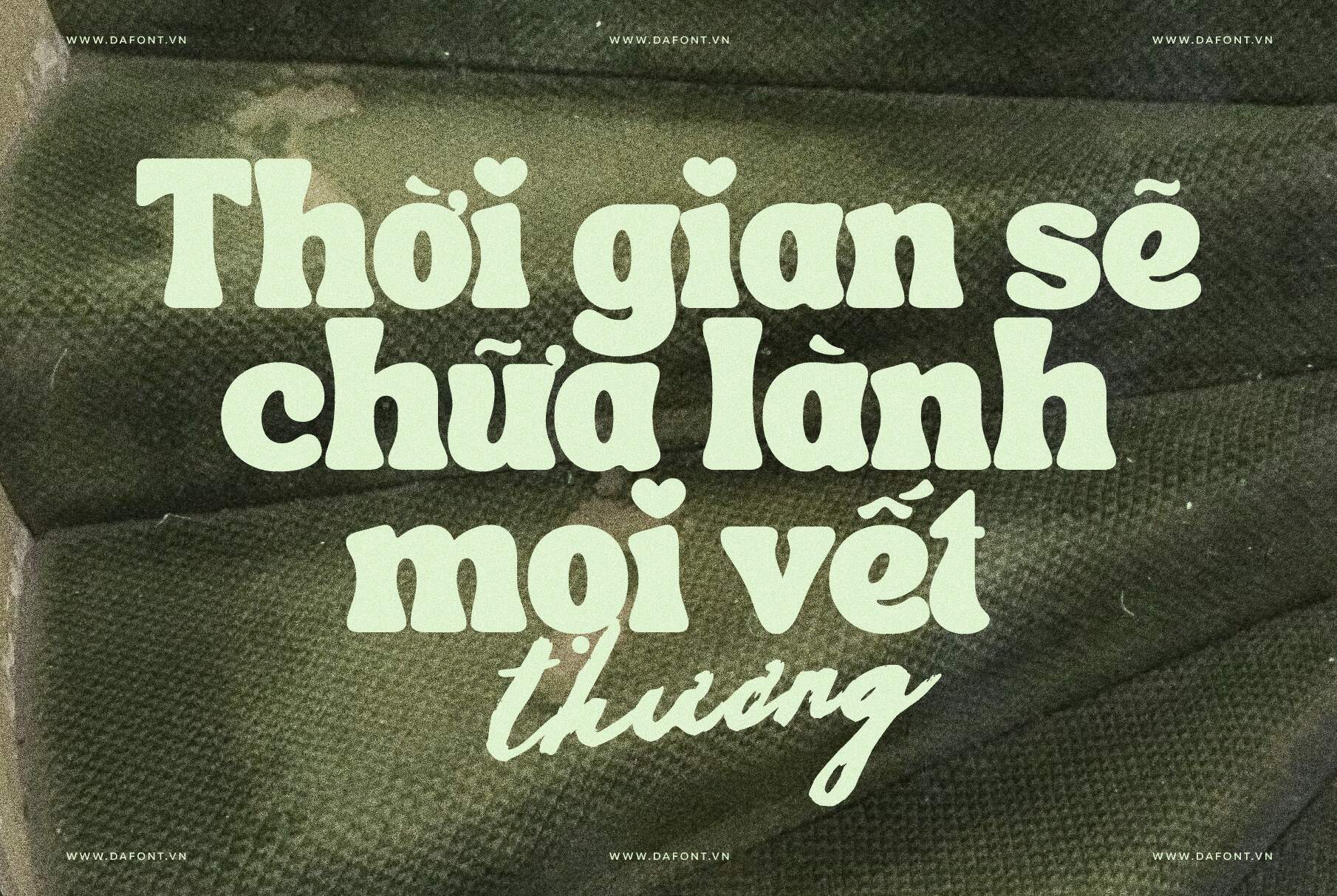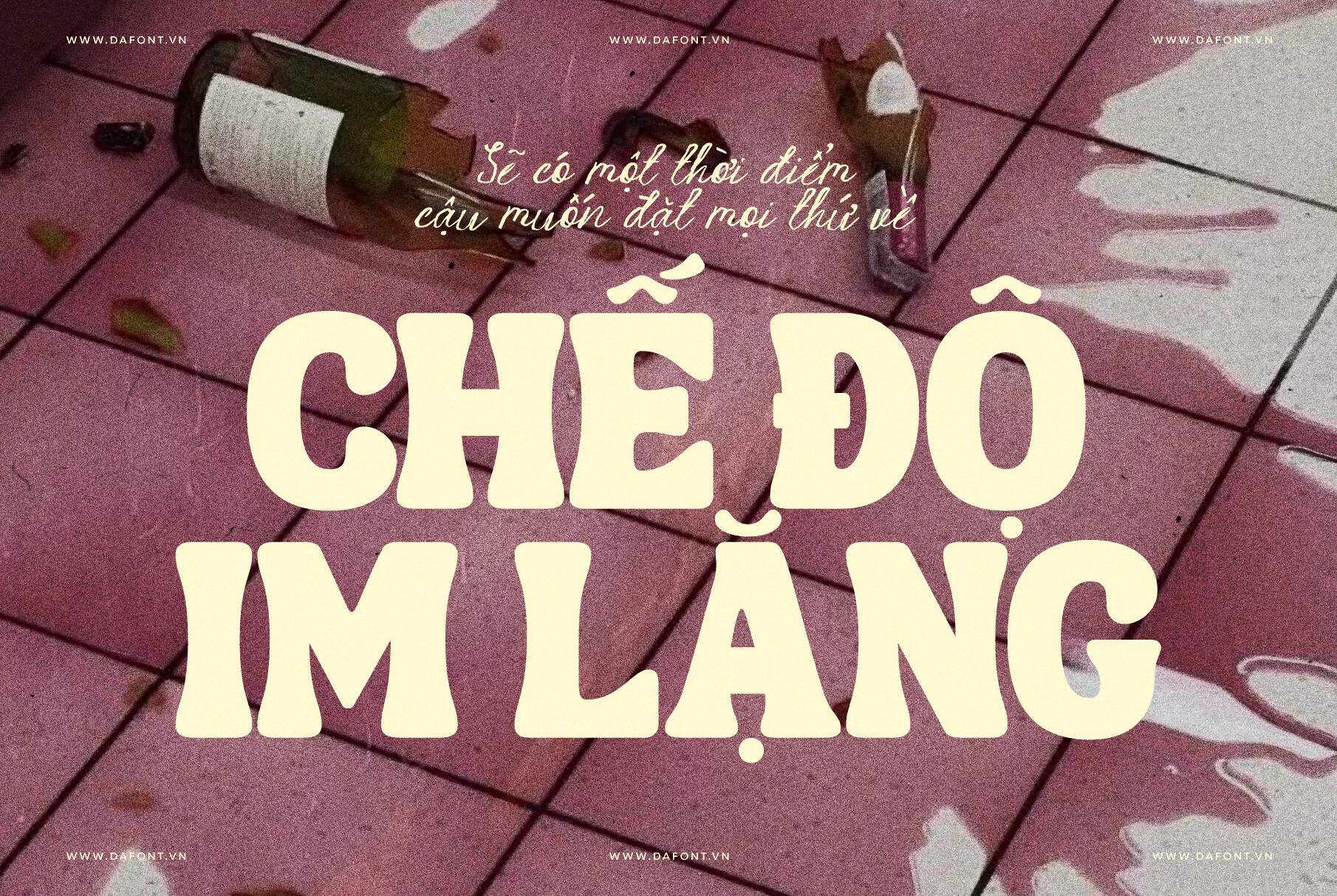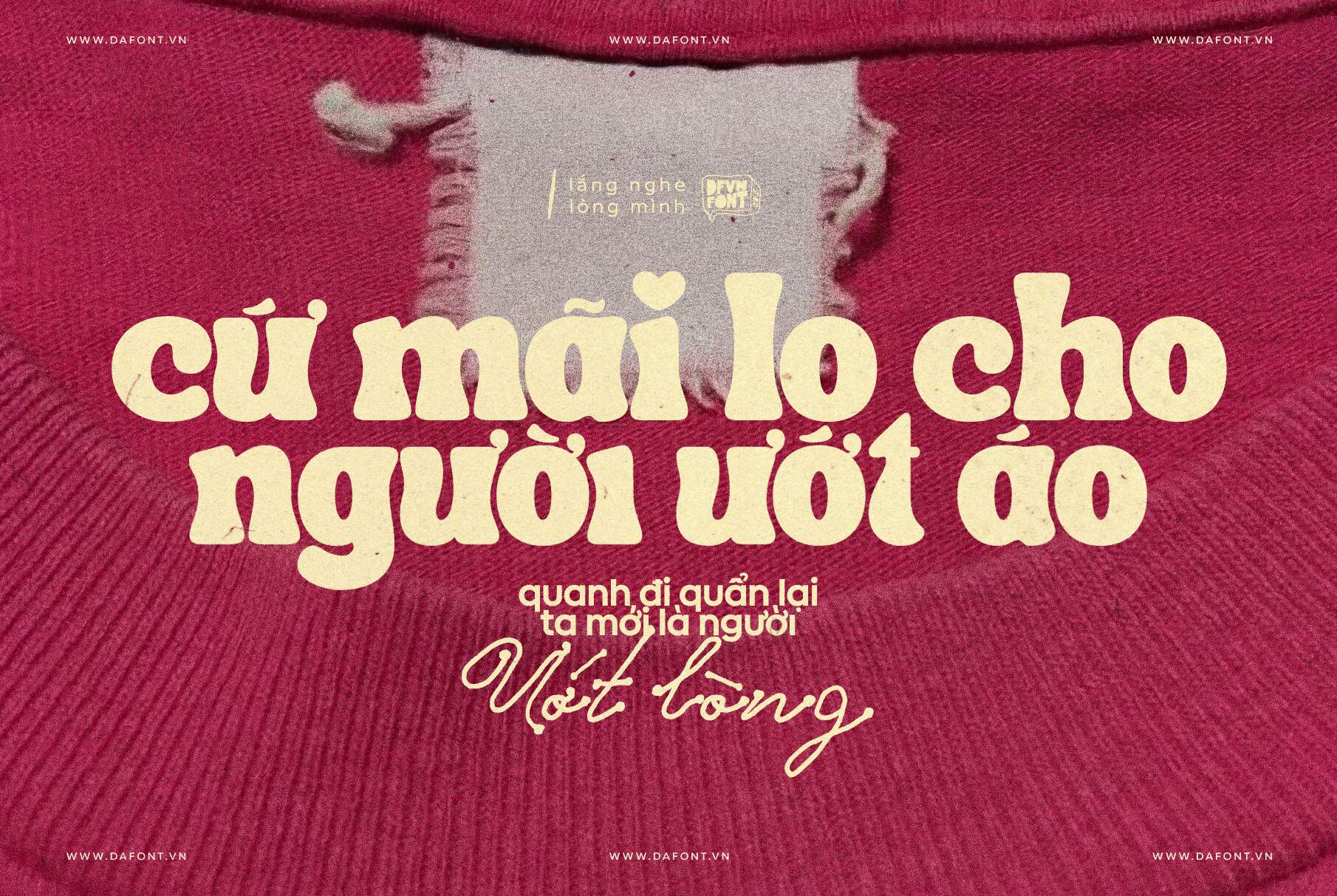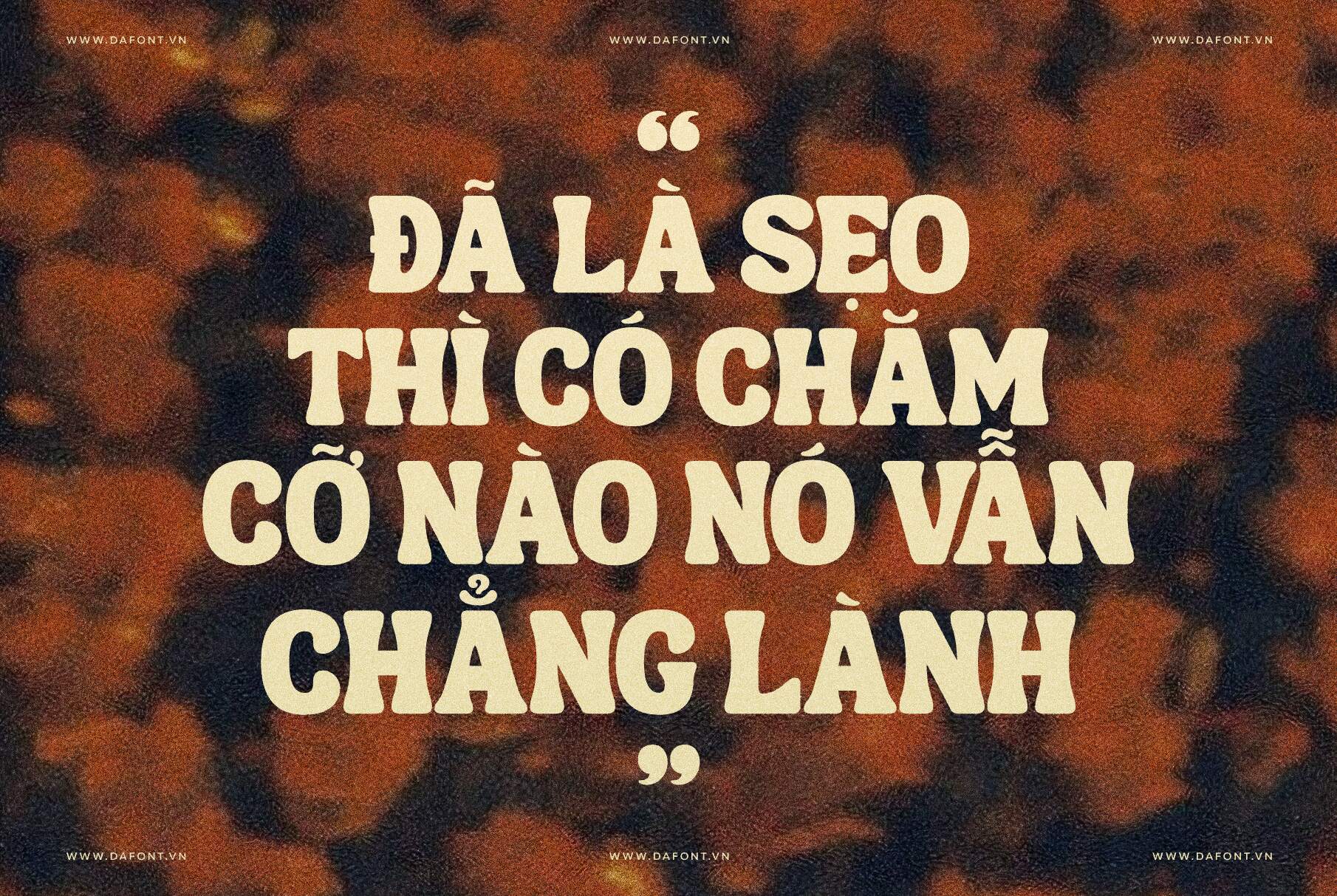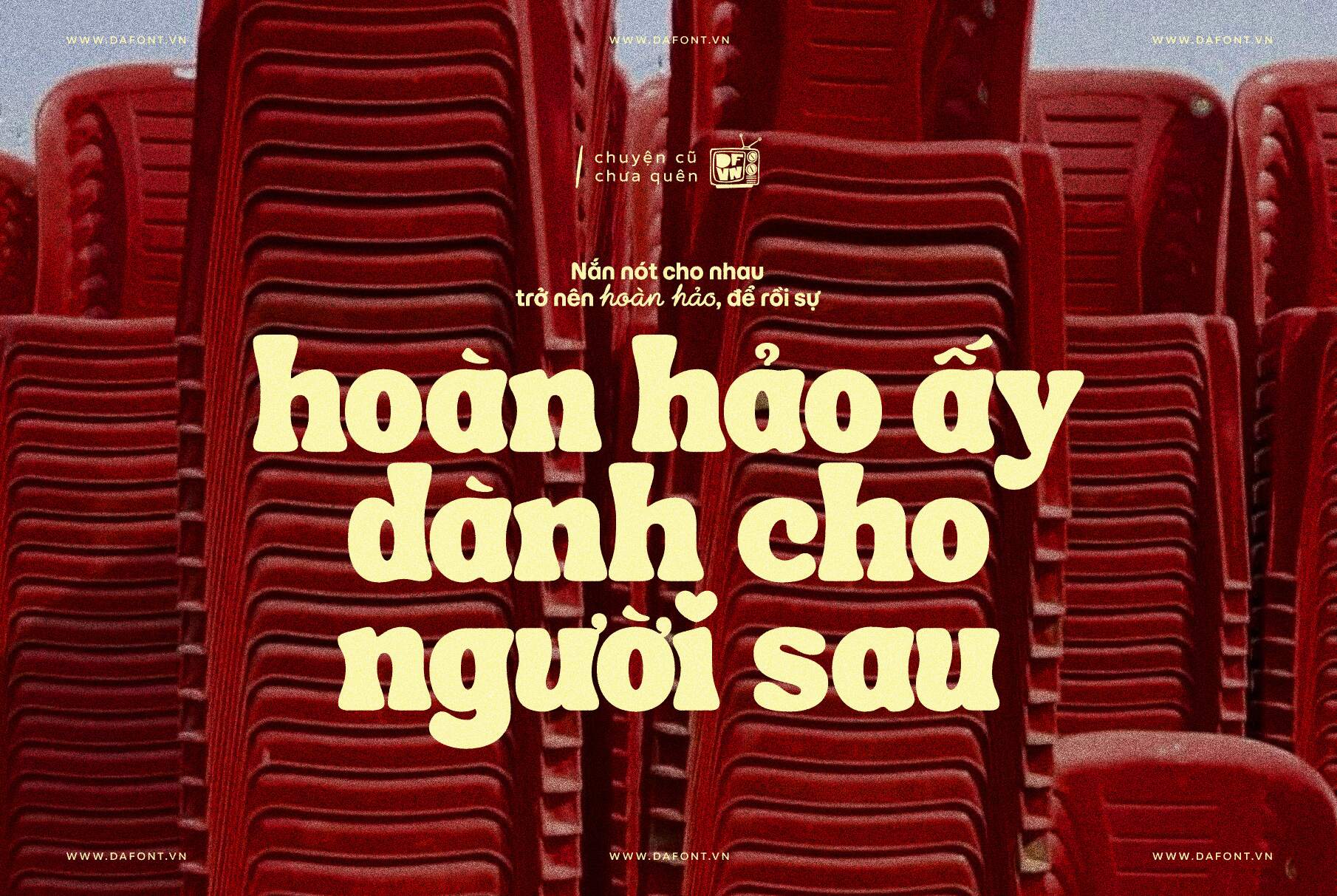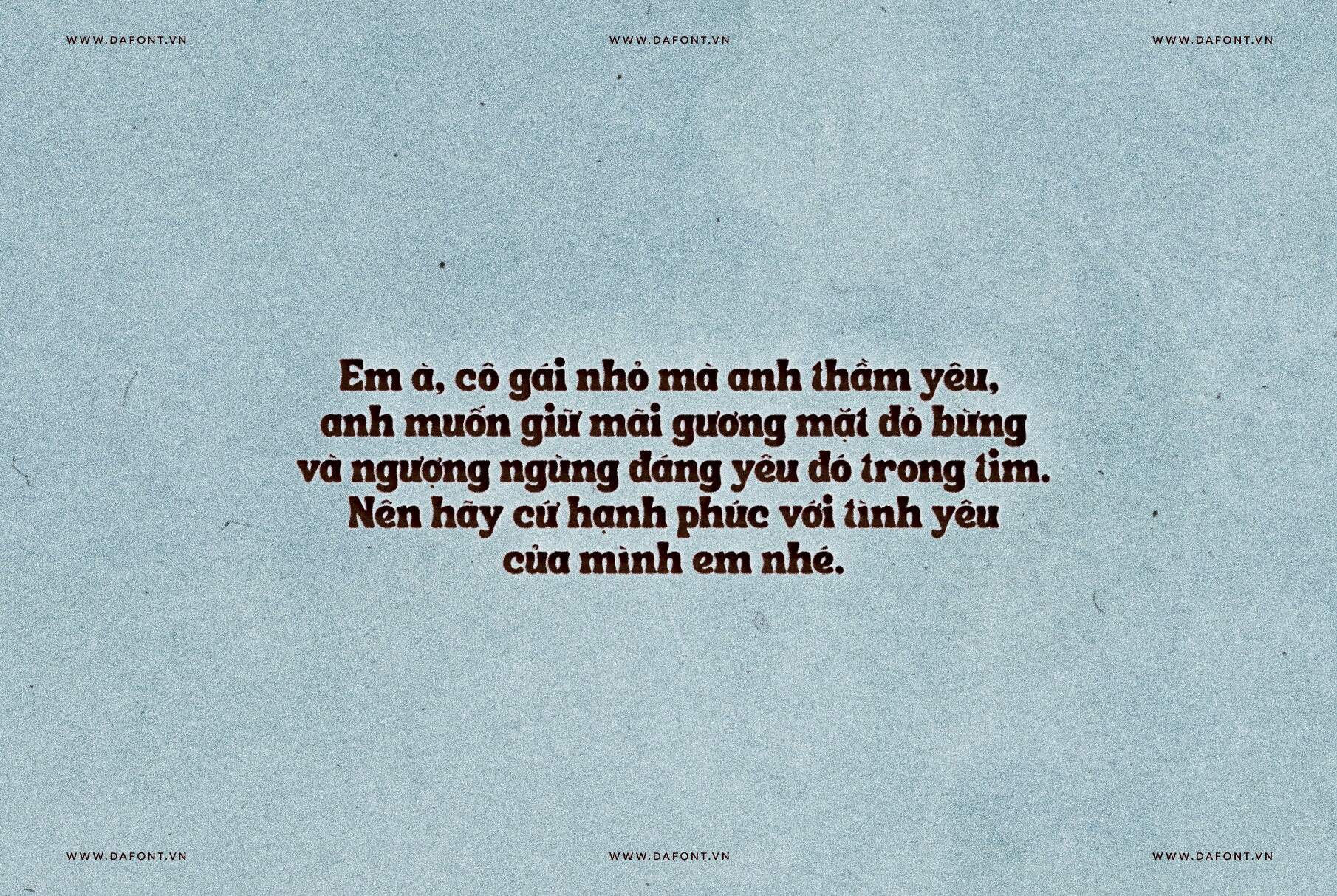
DFVN TAN – SONGBIRD
Font chữ retro 70s đẹp mê hồn cho thiết kế hiện đại
Bạn đang tìm kiếm một font chữ vừa mang hơi thở hoài cổ, vừa có nét phá cách hiện đại cho dự án thiết kế? DFVN TAN – SONGBIRD chính là câu trả lời hoàn hảo.
DFVN TAN – SONGBIRD là một font chữ display mang đậm tinh thần retro thập niên 70, nổi bật với dáng chữ đậm, khoảng cách ký tự chặt chẽ và serif mềm mại hơi phình nhẹ. Font tạo cảm giác vui tươi, có “groove” rõ rệt, rất phù hợp cho các dự án sáng tạo cần cá tính và cảm xúc hoài niệm.
Đặc điểm nổi bật của DFVN TAN – SONGBIRD
• Đường nét đậm, dày: Font sở hữu nét chữ dày, kết hợp với letter-spacing hẹp, giúp tổng thể chữ trông chắc chắn, nổi bật và rất “bắt mắt” khi dùng cho tiêu đề hoặc logo.
• Phần chân chữ (Serif) mềm mại: Phần serif được xử lý bo tròn nhẹ và phình tinh tế, không sắc cạnh. Chi tiết này tạo cảm giác thân thiện, vui tươi, đồng thời mang lại “groove” đặc trưng của phong cách retro.
• Tính linh hoạt cao: Dù mang đậm chất 70s, nhưng khi kết hợp với bảng màu pastel hoặc neon, nó ngay lập tức trở nên hiện đại và thời thượng.
• Dễ ứng dụng cho các dự án sáng tạo: DFVN TAN – SONGBIRD với cảm giác vui vẻ, phóng khoáng, rất lý tưởng cho: Dự án cá nhân sáng tạo, thiết kế giải trí, lifestyle, các thiết kế cần sự nổi bật.
Mẹo dùng DFVN TAN – SONGBIRD trong thiết kế
Để phát huy tối đa vẻ đẹp của font chữ này, bạn có thể áp dụng các mẹo sau:
• Ưu tiên dùng cho headline: Với nét chữ dày và đường nét đậm, DFVN TAN – SONGBIRD phù hợp nhất cho tiêu đề và các đoạn text ngắn, không nên dùng cho nội dung dài ở cỡ chữ nhỏ.
• Có thể sử dụng cho đoạn văn bản không quá dài: Tránh dùng font này cho các đoạn văn bản dài (body text) vì độ dày của nó sẽ gây khó đọc ở size nhỏ.
• Phối màu: Hãy thử các cặp màu tương phản đậm chất retro như: Cam cháy – Xanh Teal, Vàng mù tạt – Đỏ gạch, hoặc Hồng phấn – Xanh lá đậm.
• Kết hợp font: Kết hợp TAN – SONGBIRD với một font Sans-serif mảnh và hiện đại (như Montserrat hoặc Helvetica) để tạo sự cân bằng.
DFVN TAN – SONGBIRD – Font retro 70s không thể bỏ qua
DFVN TAN – SONGBIRD font là lựa chọn lý tưởng cho những nhà thiết kế đang tìm kiếm một kiểu chữ vừa hoài niệm, vừa hiện đại, vừa đủ “chất chơi” để tạo dấu ấn riêng. Với dáng chữ đậm, đường nét serif mềm mại và tinh thần 70s rõ nét, font mang đến nguồn cảm hứng mạnh mẽ cho mọi dự án sáng tạo cần sự khác biệt.
Nếu bạn yêu thích phong cách retro và muốn typography trở thành điểm nhấn chính trong thiết kế, DFVN TAN – SONGBIRD chắc chắn là một font không nên bỏ qua.